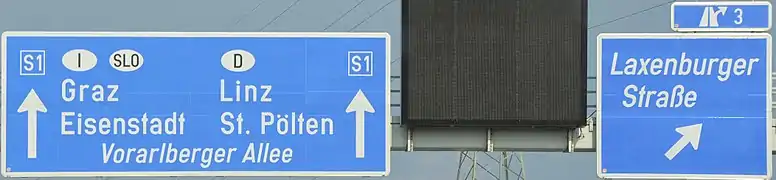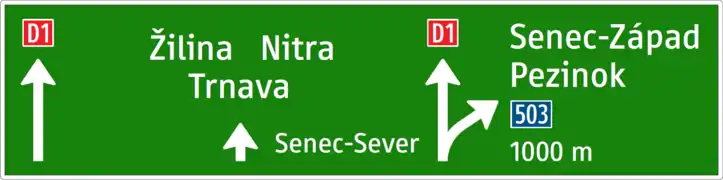
Tern (Schriftart)
Tern (Trans European Road Network; auch als TERN geschrieben) ist eine Schriftart, die im Rahmen des 6. Forschungsrahmenprogrammes als EU-Projekt „In-Safety/SOMS“[1] von der Non-Profit-Organisation International Institute for Information Design (IIID) entwickelt wurde.
Entwicklung
Der im Februar 2005 gestartete Prozess wurde im Jahr 2008 abgeschlossen. Als Ziel der neuen Verkehrsschrift wurde die europaweite Harmonisierung von statischen Verkehrszeichen und Wechselverkehrszeichen zur Darstellung von Piktogrammen und schriftlichen Informationen genannt. Die österreichische Verkehrsministerin Doris Bures nannte als Ziel in einer Anfragebeantwortung „die Erarbeitung von sprachübergreifenden und sprachunabhängigen Informationen auf Verkehrsbeeinflussungsanlagen und statischen Wegweisern auf Autobahnen“, sowie die Entwicklung der Verkehrsschrift Tern für den Einsatz auf den Standardverkehrszeichen als auch auf Matrixdisplays.
Insgesamt seien 3 000 Symbole bzw. Piktogramme gestaltet und mehreren Testreihen unterworfen worden. Die in Tern enthaltenen beiden Schriften seien „auf bestmögliche Leserlichkeit und Eignung für 20 EU-Sprachen (einschließlich Griechisch) getestet“ worden.[2] Anders als der früher üblichen Designpraxis folgend, wurde bei der Entwicklung des europaweit einsetzbaren Schrifttyps mit empirischer Evaluation gearbeitet.
Im Rahmen der Studie wurden aus 28 Verkehrsschriftarten drei der verbreitetsten und einflussreichsten europäischen Schriftarten zur vergleichenden Evaluation ihrer Lesbarkeit herangezogen.[3] Dies waren die britische Transport (Transport D und Transport 360), die holländische RWS (RWS Ee VL und ANWB Ee) und die deutsche Norm-Schrift DIN 1451 (DIN-Mittelschrift und MITT2R), dies jeweils in einer Variante für statische Verkehrszeichen und WVZ in gerasterter Ausführung mit 24 Pixel Höhe. Schriftdesignexperten verglichen Tern mit diesen Schriftarten Buchstabe für Buchstabe und analysierten ihre Vor- und Nachteile in Bezug auf die Lesbarkeit. Darüber hinaus wurde mit 122, über Annoncen aus Deutschland und Österreich als Stichprobe gesuchten Autofahrern im Doppelblind-Verfahren die Lesbarkeit der Schriften getestet. Die Probanden mussten aus zufällig dargebotenen Buchstabenreihen in den verschiedenen Schriftarten und aus unterschiedlicher Distanz die Buchstaben vorlesen. (98 Probanden brachten verwertbare Daten, 24 der ursprünglich 122 Ergebnisse mussten wegen Sehschwäche der Probanden ausgeschlossen werden.)[4]
Beteiligt an der Entwicklung waren der Österreicher Stefan Egger und der deutsche Typograf Erik Spiekermann.[5] Co-Finanziert wurde das Projekt von der ASFINAG, dem Bundesministerium für Verkehr, Innovation und Technologie und dem Österreichischen Verkehrssicherheitsfonds.[6]
Einsatz
Niederlande
In den Niederlanden wird die Schriftart seit 2009 auf elektronischen Verkehrsschildern (VMS) verwendet.[7]
Österreich
Erstmals seit Einführung der Straßenverkehrsordnung 1960 (StVO 1960) wird damit die Verkehrsschrift für Beschriftungen der Verkehrszeichen normiert. Nach der geltenden Straßenverkehrszeichenverordnung (StVZVO 1998)[2] sind bisher die nicht normierten Schriften „Breitschrift“ und „Engschrift“ auf den Verkehrszeichen aufzutragen.[Anm. 1] Die StVZVO stellt zwar in der Anlage 8 auf einem gerasterten Feld dar, wie die einzelnen Buchstaben auszusehen haben, die einzelnen Lettern sind jedoch nicht spezifiziert. Die Schilderhersteller mussten sich daher an der optischen Nachbildung orientieren. Wenn in einigen Jahren alle Schilder mit der neuen Tern ersetzt sind, soll dann das Schriftbild im gesamten Bundesgebiet einheitlich sein.
Die Schriftart Tern kommt im österreichischen Bundesgebiet seit etwa Mitte 2010 zum Einsatz.[5] Im Bundesland Oberösterreich werden Verkehrszeichentafeln mit der neuen Schrift bereits seit Mitte 2009 aufgestellt.[8] Nach Aussage der Verkehrsministerin wird zwar aktuell (Mai 2011) in ihrem Ressort „an einer allfälligen Änderung der technischen Rahmenbedingungen von Straßenverkehrszeichen“ gearbeitet. Dennoch würde auch bei einer Erlassung einer Novelle der Straßenverkehrszeichenverordnung (StVZVO) keine Verpflichtung zum Austausch aufgrund der neuen Schriftart vorgesehen werden, die über die bisherige Austauschverpflichtung nach StVO hinausgeht. Weiterhin werden also Verkehrsschilder nur getauscht werden müssen, wenn sie z. B. durch Witterungseinflüsse abgenützt sind oder wenn sie beschädigt wurden. Dadurch kommt es zu keiner Kostensteigerung durch Verkehrszeichenumrüstung und Neuaufstellung.[2] Somit ist mit einer jahrelangen parallelen Verwendung beider Schriften zu rechnen.[6]
Obwohl die neue Verkehrsschrift europaweit Gültigkeit erlangen soll, gibt es für Österreich eine Ausnahme, da für lange Ortsnamen eine engere Laufweite („Engschrift“ genannt) als die der allgemein verwendeten Schrift („Breitschrift“ genannt) zur Anwendung kommt.[8]
Schriftart „TERN“
Schriftart „Austria“
2020 wurden 65 der mit der Schriftart gestalteten Sinnbilder zur Verwendung im österreichischen Straßennetz für verbindlich erklärt.[9][10] Bereits 2019 wurden die Sinnbilder für die Autobahnen verbindlich vorgeschrieben.[11]
Slowakei
Seit April 2014 gilt die Schriftart Tern als normierte Schrift auch in der Slowakei.
- Die bisher nach der Straßenverkehrszeichenverordnung eingesetzten Schriften werden öfters als Schriftart Austria bezeichnet.